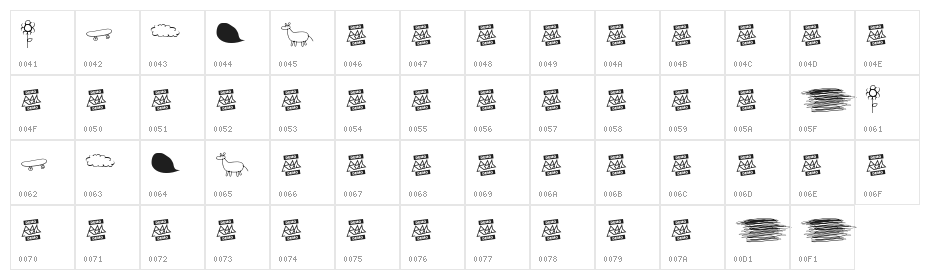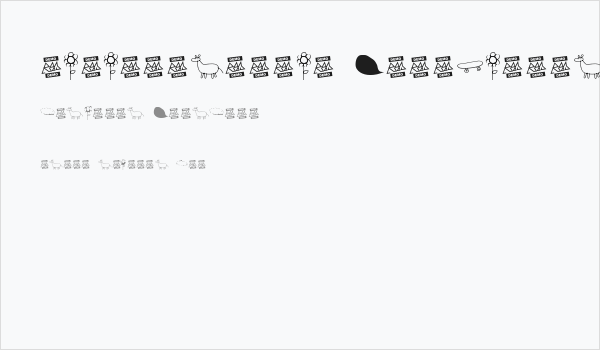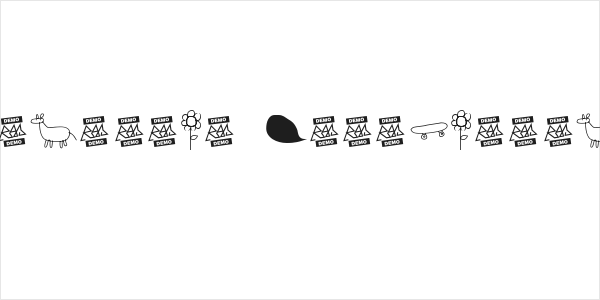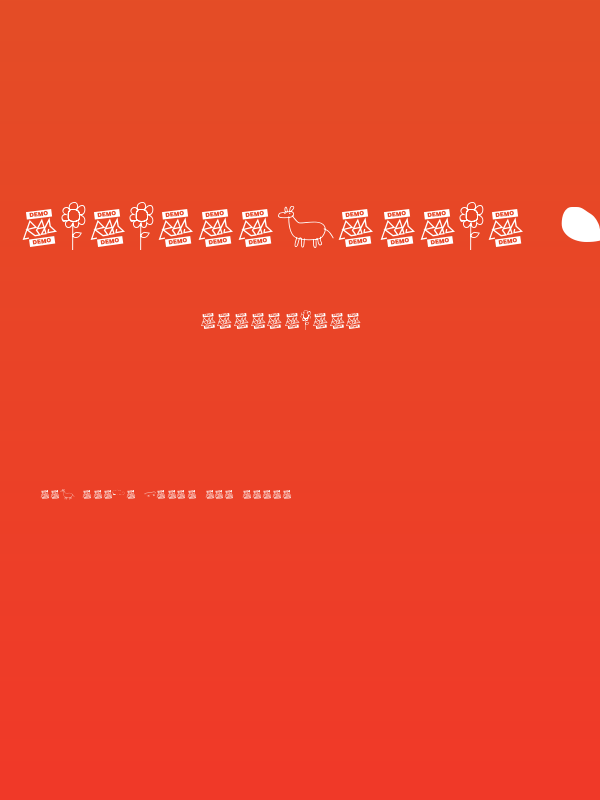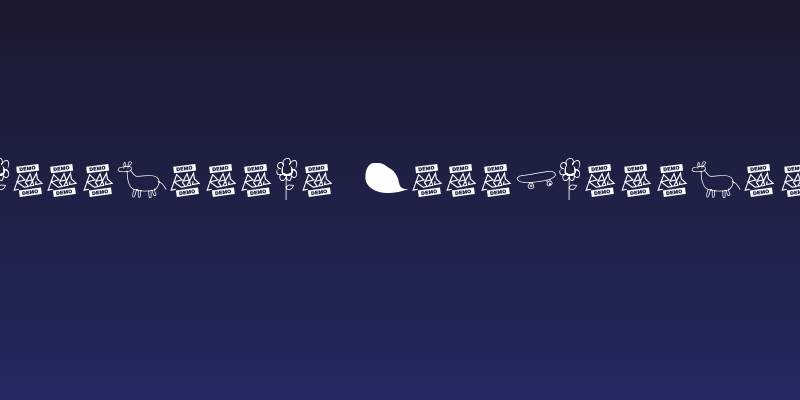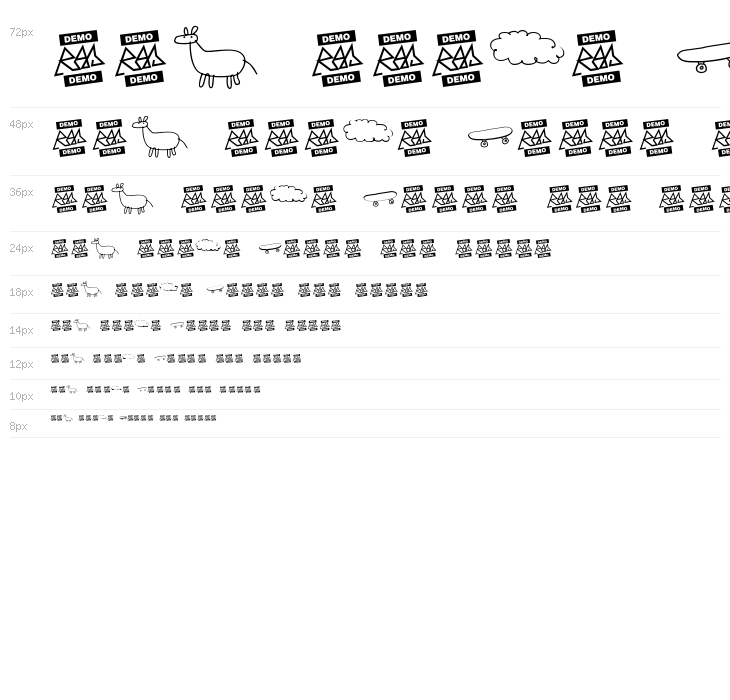
Rayairregular DingbatsRegular Font
| Estilo general | Whimsical, Playful |
| Caso de uso | Decorative elements, Illustrations |
| Proyectos propuestos | Ideal for children's books, playful invitations, creative posters, and educational materials. |